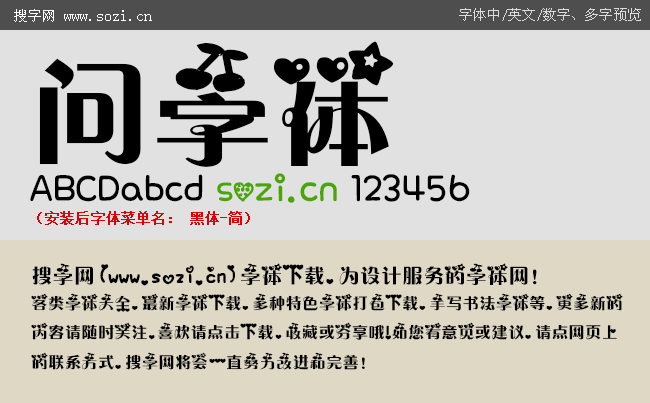
問字體
搜字網(wǎng)給大家提供一款充滿童趣的手機中文字體下載。字體名字叫問字體,這款手機字體是在粗活意字體筆畫間插入了可愛卡通圖案。粗活意是一款字形嚴肅但又非常優(yōu)美的字體,借鑒中英文草書的筆意,嚴肅中帶有靈動質感,插入卡通圖案后又增加了趣味性,適合喜歡手機字體個性一些的朋友在手機上安裝使用。